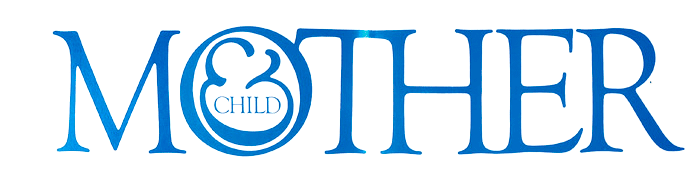
Le Maître en son Master*
Quand on oublie que le niveau du maître n’est jamais la limite à atteindre mais la barrière à sauter, il faut apprendre à dépasser les Maîtres.
Une formation n’est pas un long parcours tranquille, on y rencontre des rapides, forts en math mais pas logiques dans leur foi… et des chutes, parfois originelles, dans le choix de sa formation, rarement originales. De Charybde en Sylla, le paradis artificiel du parcours tout tracé, laisse peu de place pour tracer sa ligne, souvent plus sinueuse qu’on ne croit.
Étudiants du privé ou du public, réformés des formations, souvent elles-mêmes en perpétuelle réforme, n’ont pas le choix.
Pluri-discipline air.
Pluridisciplinaire est le Maître mot, un vieux mot, presque un gros mot, et avec lui tout le panel des maîtres à penser.
Existe-t-il des formations pluridisciplinaires sans maîtres ni disciples.
Le Master n’est pas un cap à passer mais un cap à dépasser. Pour naviguer au loin, et voir le monde de près, c’est-à-dire, aussi, à distance, avec la distance nécessaire. Mais le graphisme est une pratique qui réfléchit, en son double, comme une direction hétérogène, comme celle que la réflexion conduit.
Miroir et pensée, image et pensée, pensée imagée, image bien pensée, elle tient le produit et la production. Elle tient du reflet, en ce qu’elle reflète le monde dont elle dessine pourtant les contours. Tenir du produit et de la production c’est dépasser l’exécution, c’est maîtriser la création.
Aujourd’hui les termes s’inversent. Poursuivre ses études sans être rattrapé par elles. Changer d’air ce n’est pas l’air du temps, c’est la respiration nécessaire. Changer de parcours ce n’est pas changer de vie, c’est suivre son chemin. Repartir pour d’autres formations, avoir arrêté ses études et les reprendre, en suivre d’autres… Et demain ? On a pensé l’image de demain ?
Lorsque peter gabor oppose le monde numérique au monde «traditionnel», il craint que la démocratisation du monde numérique fasse de l’infographiste un faux créatif:
«il n’y a pas d’avenir pour les exécutants, il n’y a d’avenir que pour les créatifs».
Hier on pensé l’image manipulée, puis « technipulé ». Et demain? On a pensé l’image de demain? Ctrl Q c’est garder le contrôle.
Un des plus beaux logotypes du XXe siècle, ©herbert lubalin, mot image enceinte du sens plein de sa plénitude. On n’aura jamais fait un logo si parfait, si simple pour exprimer pleinement l’essentiel. peter gabor